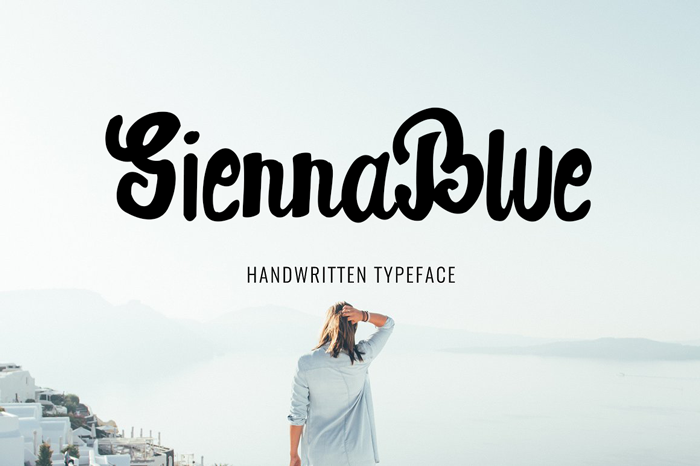
SiennaBlue Script Font – Download Grátis
A SiennaBlue é uma script livre e natural, com sua escrita não serena nem exagerada. É perfeita para adicionar um toque divertido a qualquer projeto, seja ele de papelaria, logotipos, t-shirts, impressão digital ou até mesmo em capas de música. Com seu charme próprio e versatilidade extensa, SiennaBlue é uma escolha ideal não apenas para websites com cabeçalhos, quadros de fotos, flyers e cartazes, mas também para imagens sliders e outros ambientes digitais que requerem um estilo elegante e personalizado. Seja você designer de logotipos ou webdesigner, a SiennaBlue pode ajudar a criar um design único e envolvente sem esforço, tornando-se uma ferramenta indispensável para qualquer projeto visual.